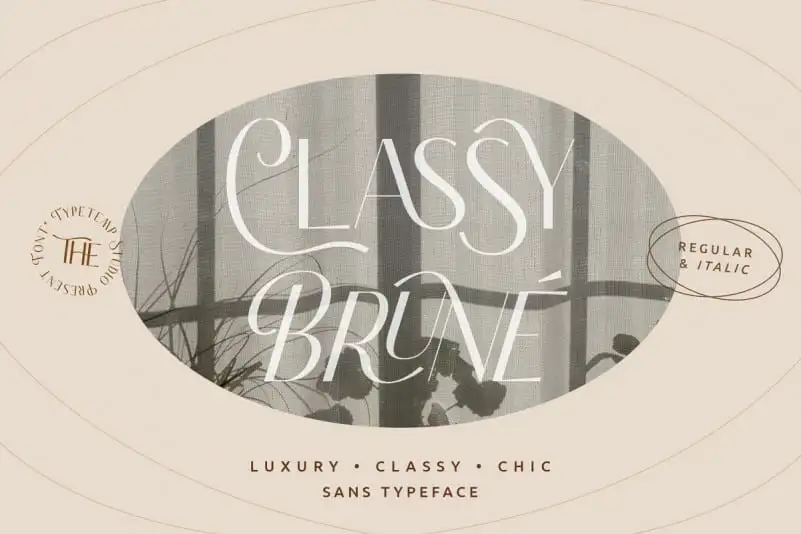
Classy Brune Sans Serif Font – Download Grátis
A Classy Brune Sans Serif é uma fonte moderna e elegante que oferece um toque sofisticado a qualquer projeto. Criada pela Typetemp Studio, esta fonte vem em duas cores: Regular e Italic, além de alternativas, ligaturas e suporte multilíngue. Perfeita para editoriais, criação de logotipos, branding de roupas, embalagens de produtos ou cabeçalhos de revistas, ela também é ideal como overlay de texto estiloso em qualquer imagem de fundo. Repleta de luxo e elegância visual, esta fonte oferece um equilíbrio perfeito entre a modernidade e o refinamento. É uma escolha ótima para aqueles que buscam uma combinação arrojada de estética sofisticada em projetos digitais ou impressos. Com sua versatilidade, ela se adapta a diversos estilos de design, tornando-a uma fonte indispensável para qualquer designer gráfico profissional.